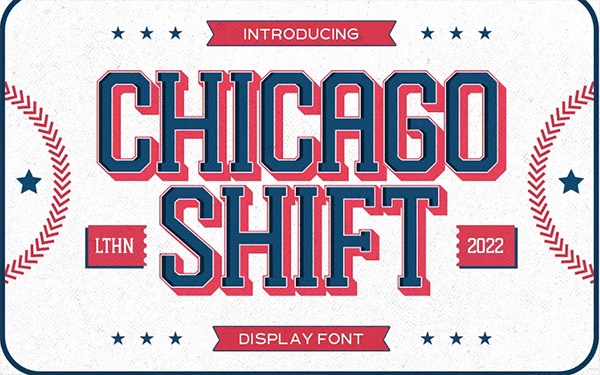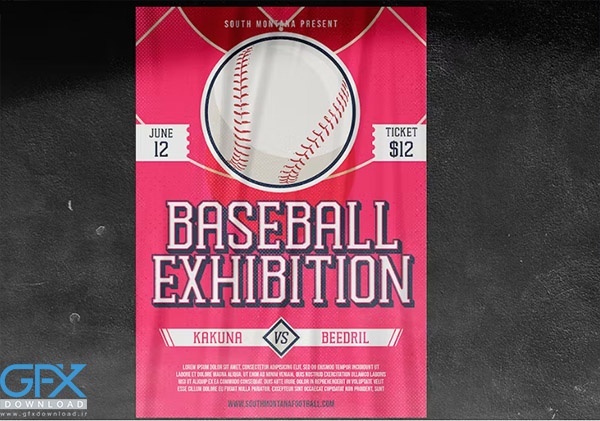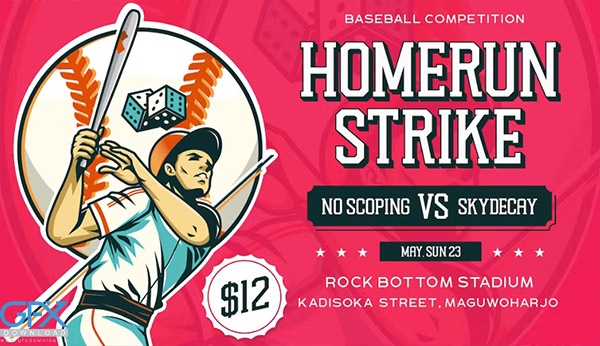
فونت ورزشی Chicago Shift
فونت انگلیسی ورزشی Chicago Shift
Chicago Shift یک فونت تخصصی است که برای تم ورزشی ساخته شده است. بسیار مناسب برای تیتر، لوگوتایپ، پوشاک، دعوت نامه، برندسازی، بسته بندی، تبلیغات و غیره با مضمون قدیمی و همچنین مدرن. این فونت ورزشی Chicago Shift در حروف بزرگ، کوچک، علائم نگارشی، نمادها و اعداد، مجموعه سبک متناوب، لیگاتورها و غیره نیز از چند زبانه و از قبل کدگذاری شده PUA پشتیبانی می کند.
فونت انگلیسی با تم ورزشی Chicago Shift
• نام فونت: Chicago Shift
• اعداد و علائم نگارشی
• چند زبانه
• متناوب و لیگاتورها
• PUA کدگذاری شده است